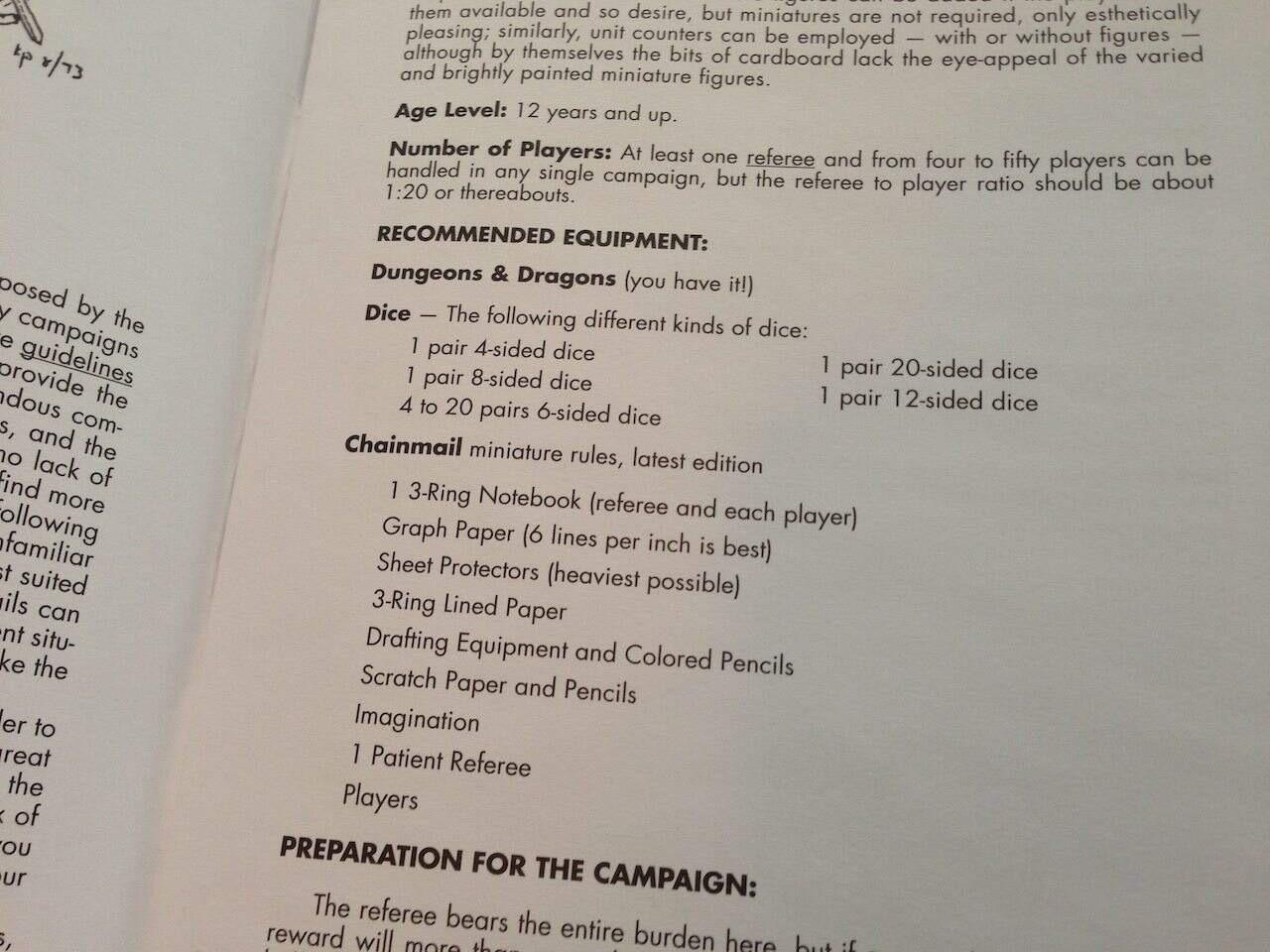
Anti-Futurismus
Hallo, ich denke ich fange meine Forenmitgliedschaft hier mal zweckdienlich mit einer Frage an:
Ich spiele mich zur Zeit mit einem privaten Projekt das in Wort und Bild ein bisschen eine Homage an alte Publikationen aus den 70ern/80ern erinnern, und da gab es dann Futura als Brotschrift. Bei aller Nostalgie möchte ich das nun eher vermeiden, aber doch noch einen gewissen Charakter mitnehmen.
Ich dachte schon an eine Slab Serif, aber da wir die momentan im Web so viel sehen, befürchte ich, dass das dann zu modern auf manche Leser wirken würde.
Komme ich dem Ziel nun mit einer lesbareren Serifenlosen oder einer "Futura-artigen" Serifenschrift näher? Oder ist das Unterfangen generell unlösbar?
Ist ein Hobby-Projekt, mein Budget neigt also nicht zu den teuersten Varianten, aber man muss sich nicht auf freie Fonts beschränken.
Ein weites Feld und eine diffuse Frage. Die zeittypischen Typomoden der 70er unterscheiden sich schon sehr von denen der 80er ... schon deshalb wären das ein paar Fliegen zu viel, um sie auf einmal zu erschlagen.
Und dann isses natürlich immer eine Entscheidung, ob ich einen Stil oder eine Mode oder einen Zeitgeschmack interpretieren will oder persiflieren oder karikieren oder zitieren möchte.
"Futurismus" hat übrigens mit der Futura genausowenig zu tun, wie die Futura eine typische Schrift der 70er oder 80er Jahre wäre ... Zumal es bei zeittypischen Schriften sicherlich auch einen geografischen Aspekt gibt. Ganz so pseudo-globalisiert-einheitlich wie heute ging es in diesen Jahrzehnten noch nicht zu.
Deshalb ist es leider (zumindest m.E.) ziemlich unmöglich, sachdienliche Antwort zu geben. Vielleicht könntest Du das Anliegen etwas präziser beschreiben?
Das mit dem Futurismus war auch eher als Wortspiel gedacht. Spezifisch genug im Titel kann man hier wenig werden, und dann kam wohl das Spielkind durch.
Aber danke, beim Neu lesen ist es recht offensichtlich wie der Satz falsch gelesen werden kann. Ich meinte jetzt nicht, dass ich eine generische Publikation aus den 70ern/80ern imitieren möchte und dass damals generell Futura angesagt war. Der historische Kontext tut eigentlich nicht viel zur Sache, ausser dass hier etwas Nostalgie mit spielt, die aber nicht zu weit gehen sollte. Visuelle Anlehnung ist okay, aber es sollte sowohl etwas Eigenarbeit einfließen, als auch die Lesbarkeit etwas optimiert werden.
Konkreter: Die "Vorlage" sind die Original Dungeons & Dragons Bücher (ein Rollenspiel). 18x13 Bücher, einspaltiger Futura Satz. Als Corona/Nostalgie Projekt versuche ich hier eine Art angepasste "Neuauflage", auch um meine Layout-Kenntnisse mal wieder etwas zu strecken, nach Jahren wo das nur bei (Programmierer-)Webdesign endete. Ich bin da nicht der einzige, es gibt viele Ergänzungen und Neu-Interpretationen, oft dann fast sklavisch am Original und damit an Futura festhaltend.
Sind dann auch (bis auf den Buchtitel) nur die zwei Futura Schriftgrade. Muss bei meiner Version nicht zwanghaft sein.
Nähme ich jetzt meine "Erfreuliche Drucksachen" Fibel zur Hand, käme da jetzt wohl eine altmodischere Serife ins Spiel, und wahrscheinlich rein objektiv auch die bessere Wahl. Aber es gibt ja sicher etwas zwischen Original und solch einer Abweichung.
Ich würde ja mal schauen, ob nicht bei den Schriften mit ähnlichem Formenprinzip etwas dabei ist …
Bei anderen geometrischen Serifenlosen stellt sich mir dann leicht die Frage, ob es die Änderung wert ist. Klar, es ist anders, aber ist es wirklich lesbarer? Da setzt die Art ja eine gewisse Grenze. Ich sehe mir gerade die Schriften der Liste an und versuche da mit den Web-Vorschauen etwas herumzuspielen, aber so wirklich beeindruckt mich nichts. Die Brandon hat eine Text Variante bei der mir am ehesten noch ein Lesbarkeitsunterschied auffallen würde, hoffentlich nicht nur eingebildet. Auch die Hypatia Sans gefällt, mit OpenType bekommt man da sogar das einstöckige a, für mehr Futura-artigkeit. Ob das aber nun ein Fortschritt für die Lesbarkeit des Fließtextes ist?
Ich denke es kommt auch darauf an, was ich eigentlich "imitiert" haben will. Gehe ich ganz oberflächlich, kann ich es vielleicht einfach auf eine Serifenlose mit viel Kontrast zu der (häufigen) Halbfetten nehmen. Wenn ich die durch die Fette ersetze, kommt das bei viele Schriften so vor und ich könnte z.B. auch eine humanistische nehmen, so in Richtung Frutiger oder Syntax.
Slab Serifs hab' ich etwas probiert, aber weder sehe ich da eine gute Homage noch empfinde ich das als lesbarer.
Und eine Serife die kein kompletter Wechsel ist, entgeht mir noch. Irgendetwas das im Grauwert ähnlich kommt. Beim "Herumspielen" hatte ich einmal eine Suche nach Serifenschriften mit einstöckigem "a" laufen, und kam so zur ITC Stone Informal, die jetzt auch irgendwas hat, aber mir jetzt auch nicht so nach Fließtextschrift vorkommt.
Du solltest dir vielleicht erstmal klarmachen, was du genau willst. Bisher hast du das hier:
• es soll nostalgisch an den Charakter der Futura erinnern
• ohne sklavisch an der Futura festzuhalten
Ich vertraue den Experten hier natürlich. Wenn jetzt jemand sagt, keine Sorge, Brandon Text ist zwar auch in der gleichen Familie, aber macht der Erfahrung nach im Fließtext einen guten Unterschied was Lesbarkeit betrifft. Hier spricht meine Laien-Unsicherheit.
Und sicher, es steht fest dass ich irgendwo etwas opfern muss. Lesbarkeit ist mir das wichtigste. Verteufele ich hier die Futura zu sehr?